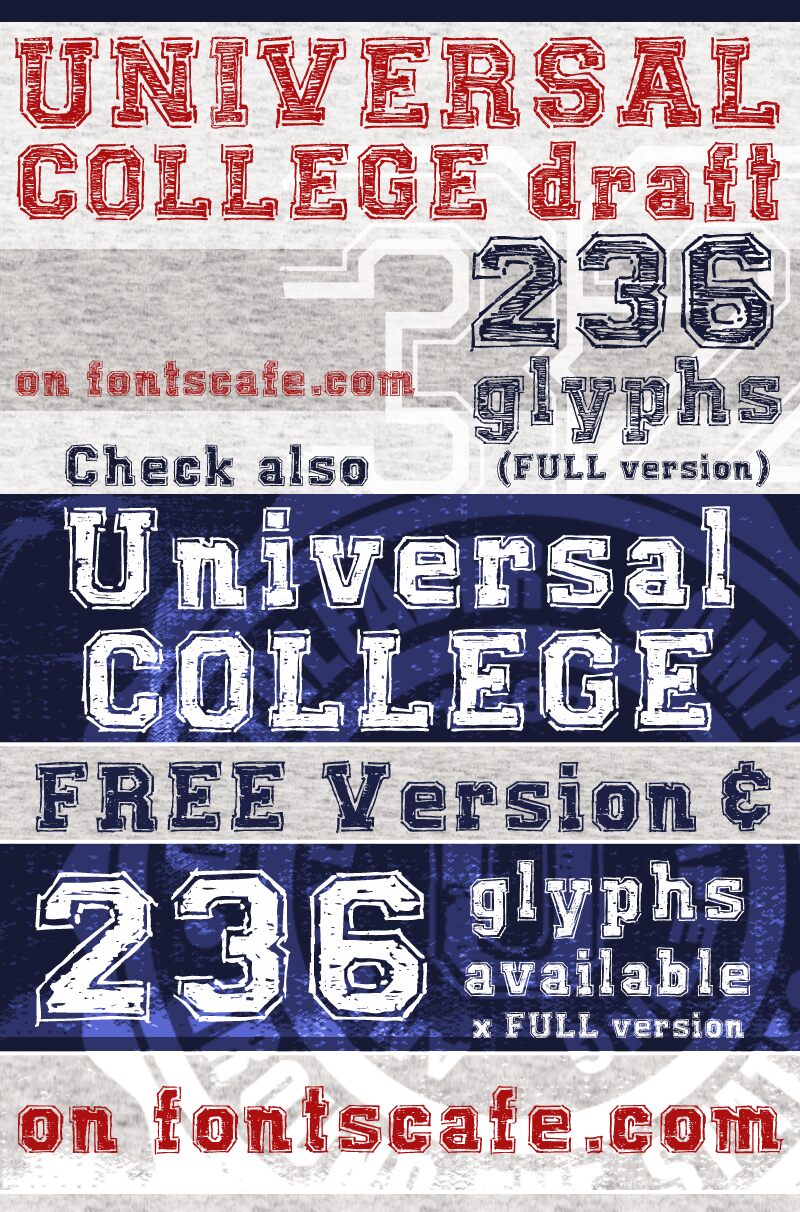
Universal College Draft, Teil der Universal College-Schriftfamilie von Fontscafe.com, ist eine Display-Schrift, die mit ihrem markanten Old-School-Charme sofort die Aufmerksamkeit auf sich zieht. Ihre kraftvolle Präsenz und ihr Retro-Stil wecken Erinnerungen an Vintage-College-Mode und klassische Sport-Insignien – die ideale Wahl für Projekte, die einen Hauch von Nostalgie versprühen sollen. Die robusten Linien und spielerischen Kurven zeugen von einem Design, das sowohl ästhetisch ansprechend als auch funktionell vielseitig ist.
Der einzigartige Charakter dieser Schriftart liegt in ihrer Fähigkeit, die Brücke zwischen traditioneller akademischer Typografie und modernen Designvorstellungen zu schlagen. Sie ist eine exzellente Wahl für Designer, die wirkungsvolle Logos, auffällige Poster oder dynamisches Team-Merchandise entwerfen möchten. Die Robustheit von Universal College Draft sorgt dafür, dass sie in Printmedien hervorsticht, während ihre klare Struktur auch bei großen Formaten für exzellente Lesbarkeit sorgt.
Ob für sportliches Branding, Materialien mit Schulbezug oder jedes kreative Unterfangen, das einen Mix aus Vintage-Flair und moderner Kühnheit erfordert – Universal College Draft verleiht Ihrer Botschaft eine unverwechselbare und einprägsame Note.